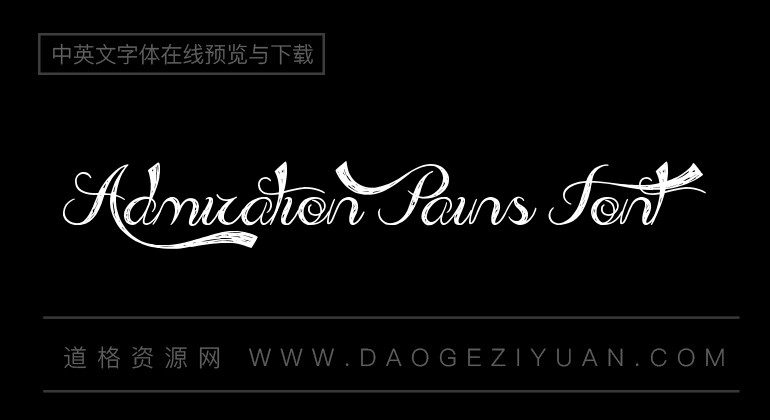
Admiration Pains Font 是一种优美的手写字体,它的设计灵感来源于简洁和自然的美感。这种字体的特点是线条自然流畅,字母间距适宜,整体看起来非常优雅。Admiration Pains Font 拥有多种字重和变体,适合用于设计海报、卡片、标志、包装等场合。此外,这种字体也可以用于网站、博客或社交媒体的排版,使文本更加易读且具有个性和艺术感。Admiration Pains Font 还支持多种语言,包括英语、西班牙语、德语、法语等等,因此可以满足不同用户的需求。内容介绍
Admiration Pains Font是一款非常不错的手写艺术字体,具有很好的视觉感,适合于文化类的宣传设计、商业类品牌的广告和产品包装设计以及个性化文字排版等较多场景。